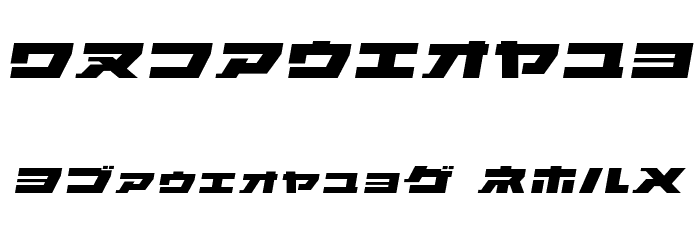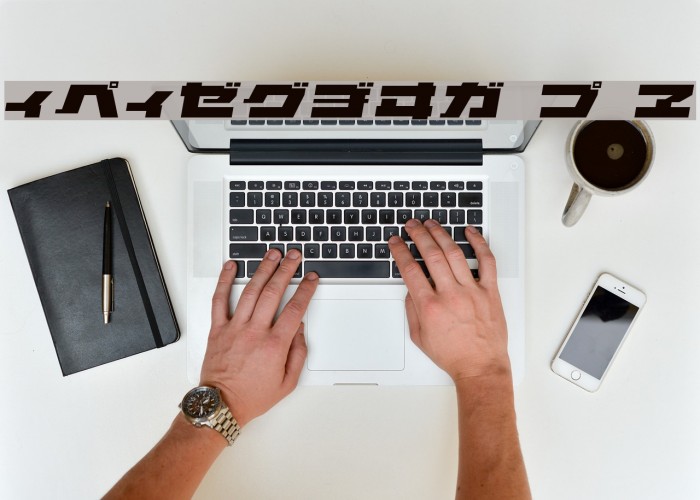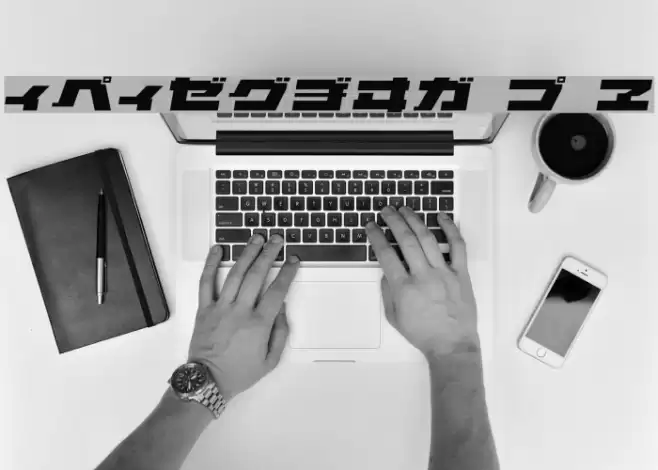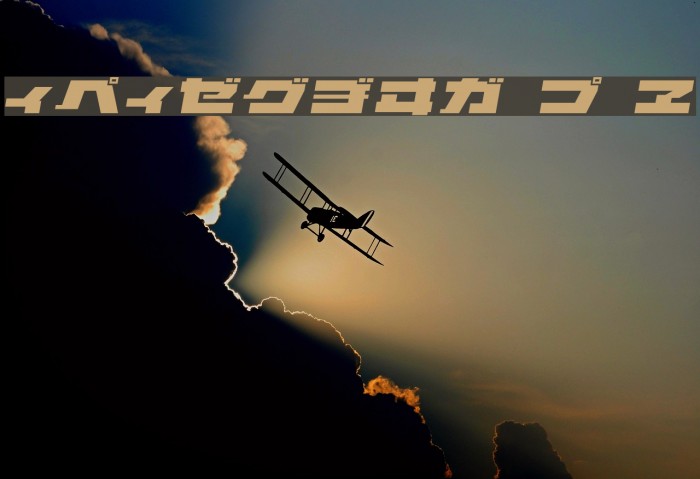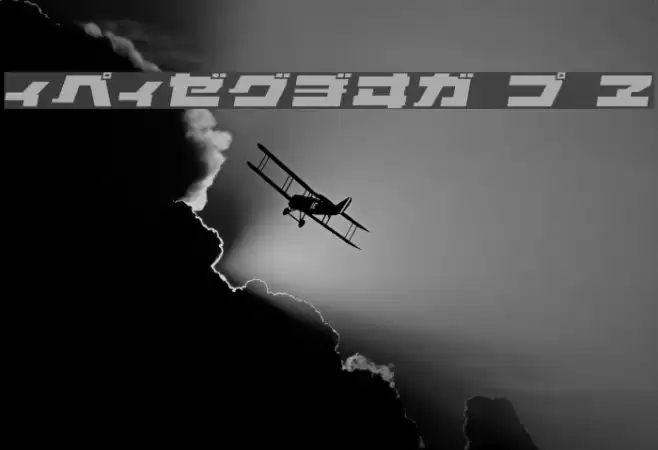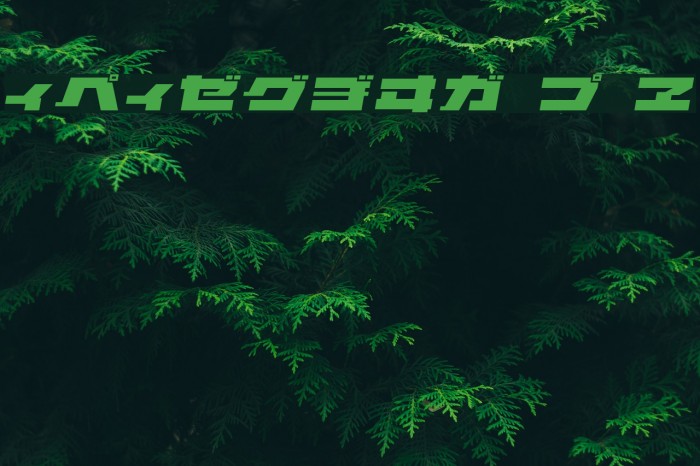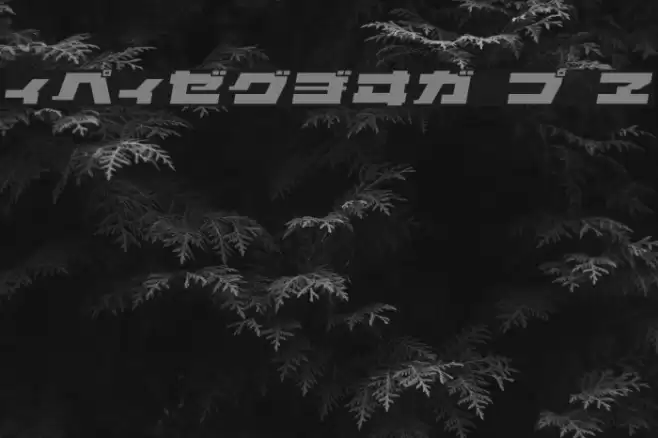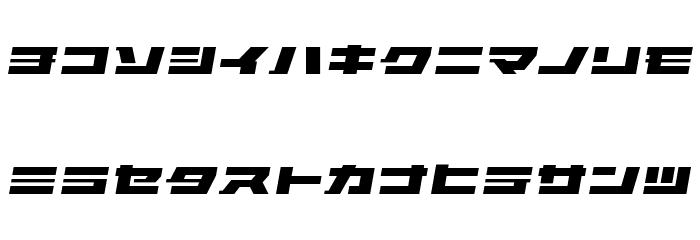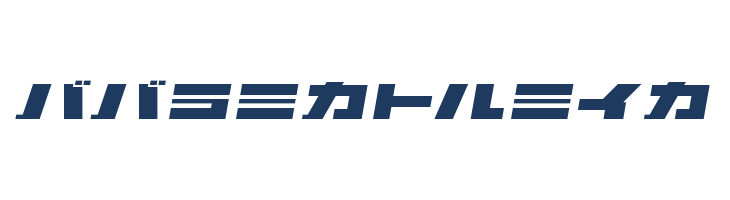
ELEPHANT K Oblique Font
| 全体的なスタイル | Futuristic |
| おすすめプロジェクト | Ideal for sci-fi themed posters, video game titles, technology branding, and dynamic logo designs. |